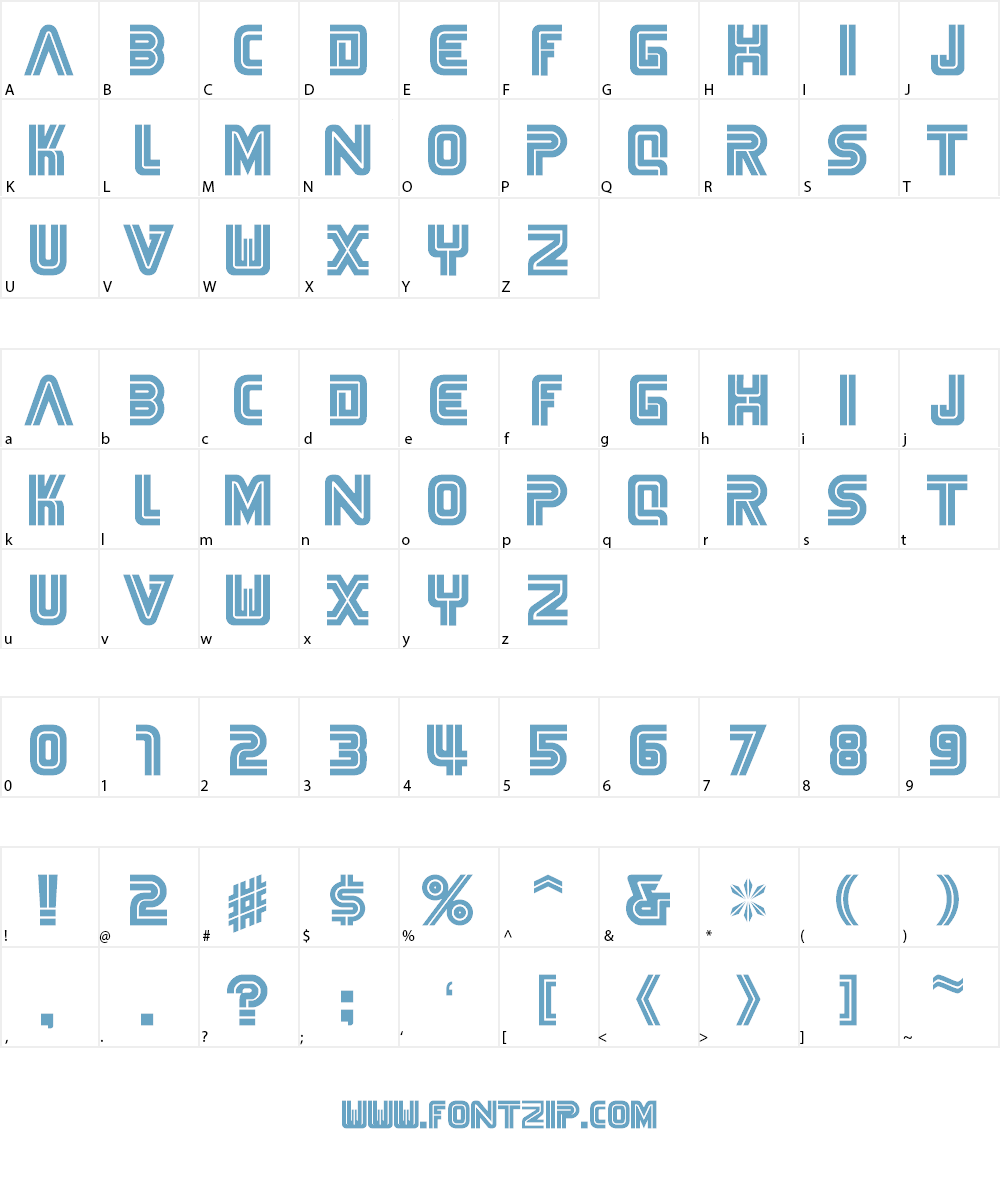
El Sr. Robot es una serie de televisión estadounidense de suspenso y drama estrenada en USA Network el 24 de junio de 2015. La serie cuenta la historia de Elliot Alderson, un joven que vive en la ciudad de Nueva York, que trabaja en la empresa de seguridad cibernética Allsafe como ingeniero de seguridad .
El eslogan "Nuestra democracia ha sido pirateada" en el póster está ambientado en Din Black , y el logotipo del programa de televisión es muy similar a una fuente llamada Mr. Robot, que es una fuente creada por fans basada en el logotipo. Puedes descargar la fuente gratis aquí .